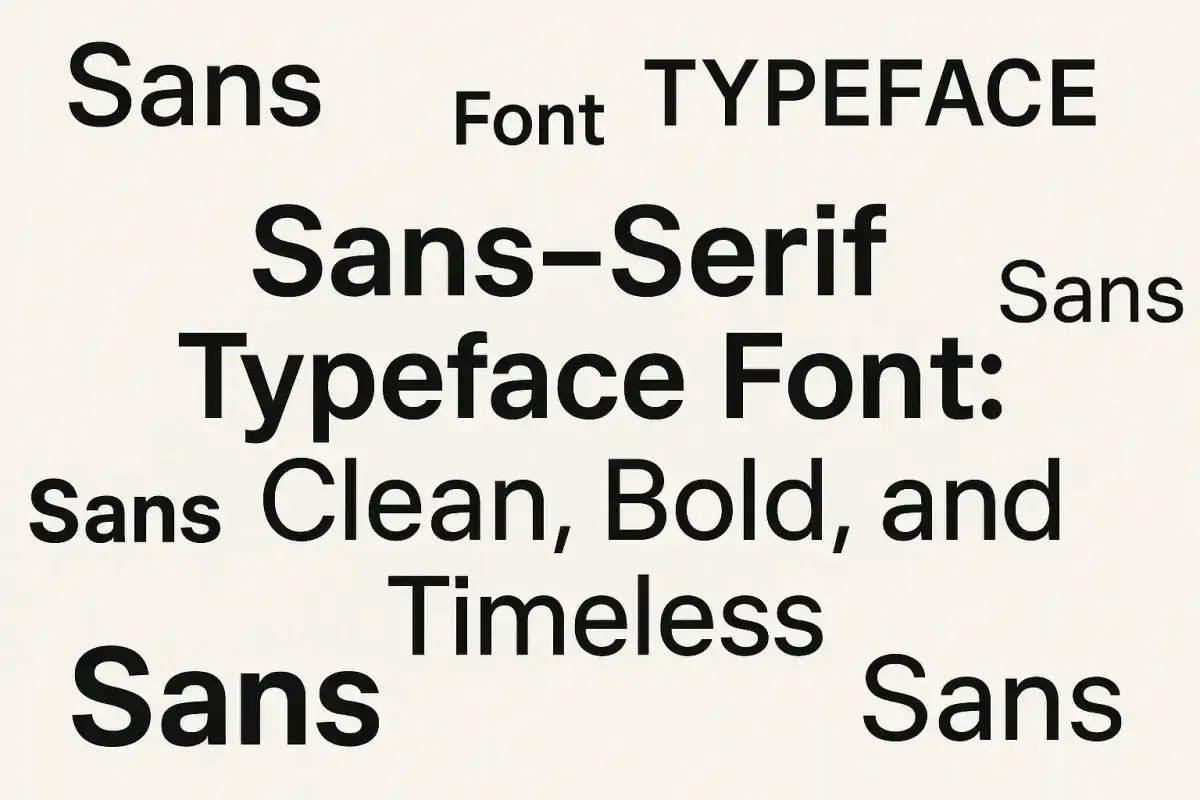
Prosta czcionka - Jak wybrać idealny krój do druku i online?
Prosta czcionka nie jest jednym konkretnym fontem, tylko całym sposobem projektowania liter: bezszeryfowym, uporządkowanym i nastawionym na czytelność. W praktyce liczą się proporcje znaków, odstępy, ciężar kreski oraz to, czy krój dobrze wygląda zarówno na etykiecie, jak i w firmowym dokumencie. W tym tekście pokazuję, jak rozpoznać minimalistyczne kroje pisma, kiedy wybrać je do druku lub internetu i na jakie pułapki uważać przy codziennej pracy z typografią.
Minimalistyczny krój ma być czytelny, neutralny i dobrze pracować w różnych formatach
• Najważniejsze są: otwarte kształty liter, dobre odstępy, umiarkowany kontrast i pełne polskie znaki.
• W materiałach biurowych najlepiej sprawdzają się kroje bezszeryfowe o spokojnym rytmie, a nie ultracienkie ozdobniki.
• Do ekranów warto wybierać fonty projektowane z myślą o interfejsach, a do druku modele o stabilnym rysunku kreski.
• Najlepszy test to podgląd w realnym rozmiarze: 10-12 pt w druku i 14-16 px w treści internetowej to dobry punkt startowy.
• Prostota działa najlepiej wtedy, gdy wspiera treść, a nie udaje charakter samą „czystością” formy.
Czym wyróżnia się minimalistyczny krój pisma
W typografii lepiej mówić o kroju pisma niż o samej czcionce, ale w codziennym języku oba określenia funkcjonują obok siebie. Minimalistyczny krój rozpoznaję po tym, że usuwa wszystko, co zbędne: nie ma ozdobnych szeryfów, nie przeciąża liter dekoracją i nie robi z tekstu wizualnego hałasu. Dzięki temu łatwiej buduje spokój, porządek i nowoczesny charakter.
To jednak nie znaczy, że każdy prosty font wygląda tak samo. Jedne są geometryczne, jakby zbudowane z koła i prostokąta, inne humanistyczne, czyli bardziej miękkie i bliższe naturalnemu ruchowi ręki. Ja zwykle patrzę przede wszystkim na trzy rzeczy: otwartość znaków, wysokość małych liter i odstępy między literami. Jeśli te elementy są dobrze ustawione, tekst oddycha i pozostaje czytelny nawet wtedy, gdy projekt jest oszczędny.
W praktyce ważne są też detale, które na pierwszy rzut oka łatwo przeoczyć. Dobre minuskuły, czytelne polskie ogonki, wyraźne różnice między podobnymi literami i brak zbyt ciasnego kerningu robią większą różnicę niż modna nazwa kroju. To właśnie te cechy decydują, czy font będzie tylko „ładny”, czy naprawdę użyteczny. Z takiego rozróżnienia płynnie przechodzimy do konkretnych przykładów.
Najciekawsze minimalistyczne kroje do pracy biurowej i cyfrowej
Nie szukam tu fontów efektownych na jeden plakat. W pracy redakcyjnej i przy materiałach firmowych liczy się raczej stabilność, czytelność oraz to, jak krój zachowuje się w dłuższym tekście, na etykiecie, w prezentacji i w interfejsie. Poniższe przykłady dobrze pokazują, że prostota może mieć różne odcienie.
Krój Charakter Gdzie sprawdza się najlepiej Na co uważać
Inter Neutralny, ekranowy, bardzo uporządkowany Strony internetowe, panele, dokumenty, instrukcje Przy zbyt małym rozmiarze i cienkiej wadze może stracić wyrazistość w druku
Manrope Lekki, otwarty, nowoczesny, ale nie chłodny Branding, prezentacje, nagłówki, identyfikacja wizualna W długich blokach tekstu wymaga dobrze ustawionych odstępów i kontrastu
Open Sans Spokojny i uniwersalny, bez przesady Biuro, formularze, treści użytkowe, materiały informacyjne Nie buduje mocnego charakteru, więc bywa zbyt neutralny dla marek premium
Roboto Techniczny, geometryczny, ale z przyjaznymi krzywiznami UI, aplikacje, instrukcje, systemy dokumentów Przy słabym doborze grubości może wydać się zbyt zwyczajny
Source Sans 3 Porządny, czytelny, lekko redakcyjny Dłuższe teksty, materiały szkoleniowe, wydruki wewnętrzne W logotypie może być zbyt zachowawczy, jeśli marka potrzebuje więcej osobowości
Montserrat Bardziej wyrazisty, geometryczny, miejski Hasła, opisy sekcji, krótkie podpisy, nagłówki Do dłuższych akapitów bywa zbyt sztywny, jeśli nie złagodzisz go interlinią
Takie zestawienie pokazuje ważną rzecz: minimalistyczny styl nie jest jednym nurtem, tylko spektrum od miękkich, humanistycznych krojów po bardzo geometryczne formy. Helvetica i Futura nadal pozostają dla wielu projektantów punktem odniesienia, ale w codziennej pracy częściej wygrywają fonty lepiej przystosowane do ekranu i polskich warunków składu. Sama nazwa kroju nie załatwia jednak sprawy, bo o finalnym efekcie decyduje zastosowanie.
Jak dobrać font do druku, dokumentów i stron internetowych
Najbardziej praktyczny dobór zaczyna się od pytania: gdzie tekst będzie żył najdłużej? Inaczej wybieram kroj do umowy, inaczej do prezentacji, a jeszcze inaczej do strony ofertowej albo systemu etykiet. Z mojego doświadczenia najwięcej problemów bierze się z tego, że ktoś ocenia font na dużym podglądzie, a nie w docelowym rozmiarze.